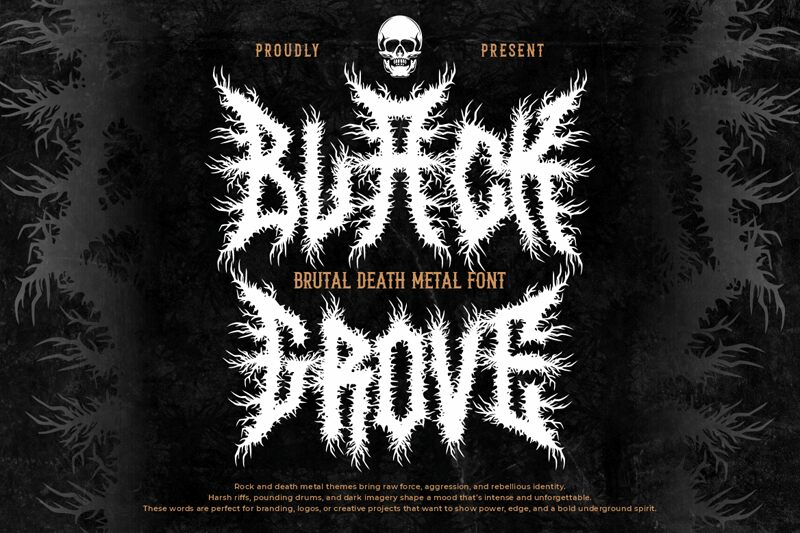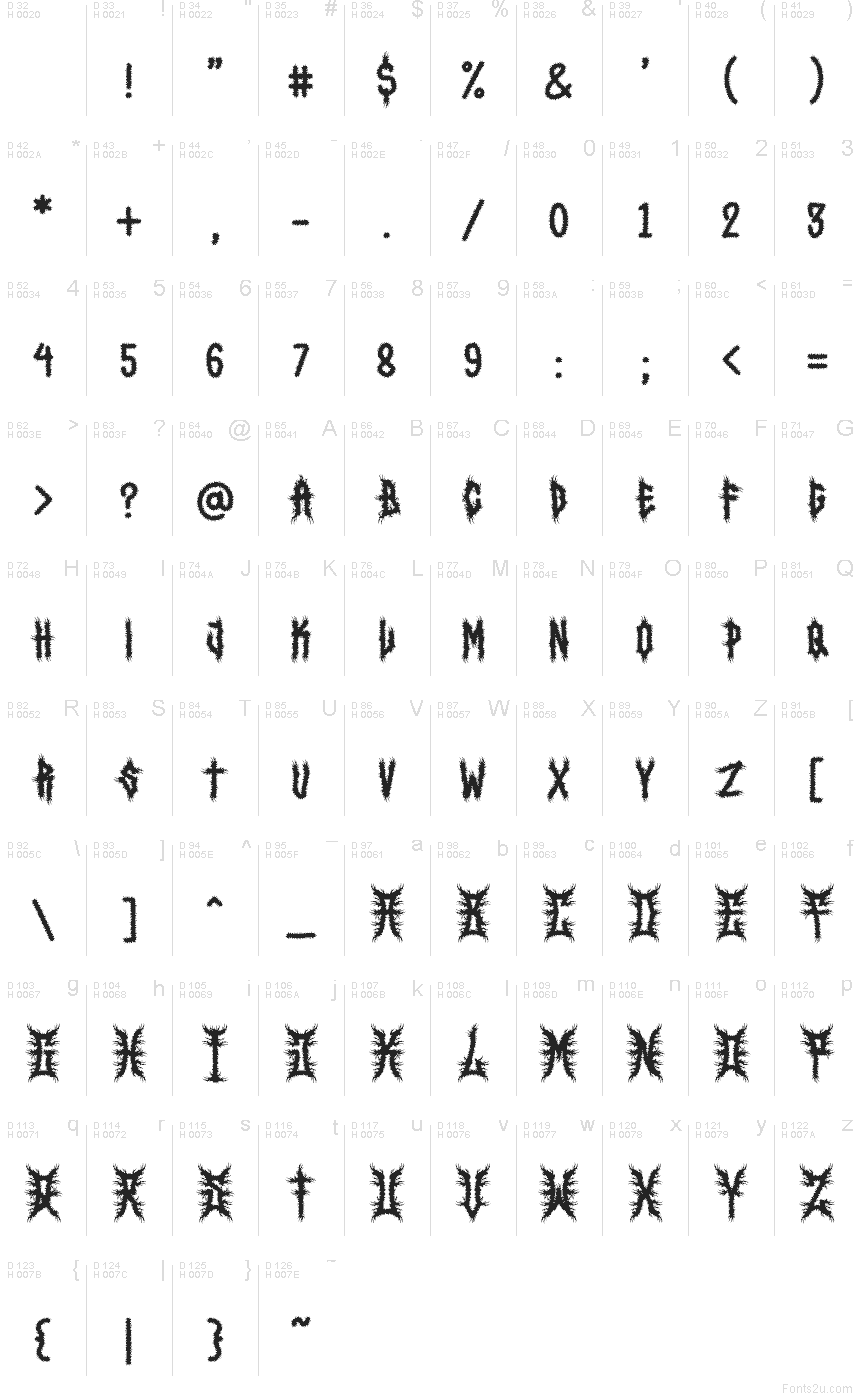
يُعد خط Black Grove من Shanaf Studio خطاً قوطياً عصرياً ومجانياً، يبدو وكأنه نما من الأشواك، وهو مشحون بطاقة موسيقى البلاك ميتال. الحروف الكبيرة تبدو خشنة ومتشابكة ووحشية بعض الشيء، حيث تنبثق من كل ضربة فروع حادة تشبه الأغصان، مما يحول هذا الخط إلى ما يشبه الشعار بدلاً من الحروف العادية.
إنه يناسب ملصقات الموسيقى، وأغلفة أفلام الرعب، وهوية العلامات التجارية للأزياء الداكنة، وعناوين الألعاب، ونشرات الفعاليات، حيث تحتاج الحروف إلى حمل الحالة المزاجية بمفردها. وباعتباره خطاً مجانياً، يعمل Black Grove بشكل رائع أيضاً في العناوين القصيرة، والرسوم الحرفية (المونوغرام)، وتصاميم المنتجات (الميرش)، لأن ملمس الأشواك الكثيف يمنح حتى بضعة أحرف طابعاً طقسياً ومشحوناً.